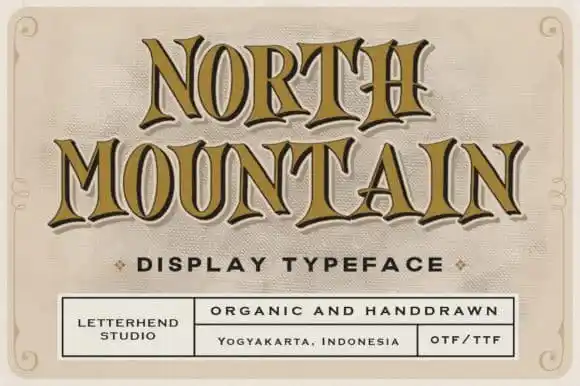
North Mountain Display Font
North Mountain Display Font é uma elegante tipografia bold e vintage com alta contração de caracteres. Inspirada no estilo das ilustrações a mão-dura dos anos 50 e 60, essa fonte traz um toque sofisticado e distinto para qualquer projeto. Perfeitamente projetada para destacar seus ideias criativas e levar seu trabalho para além do usual, essa tipografia é uma escolha perfeita para escrita de designs web, criação de cartões empresariais ou qualquer outra coisa que necessite de um toque único. Com apenas dois cliques no mouse, você pode transformar suas ideias em realidade e criar algo realmente extraordinário. North Mountain Display Font traz uma nova dimensão à sua marca digital e física.